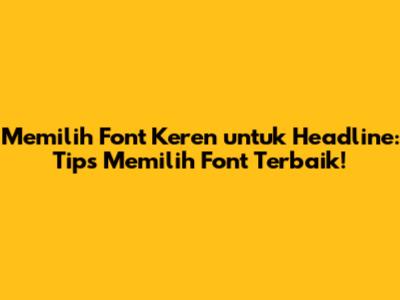
- Times New Roman: Font klasik yang selalu menjadi pilihan aman.
- Georgia: Font serif yang lebih modern dan mudah dibaca di layar.
- Merriweather: Font serif yang elegan dan cocok untuk headline artikel berita.
- Playfair Display: Font serif yang mewah dan cocok untuk headline artikel fashion atau lifestyle.
- Arial: Font sans-serif yang paling umum dan mudah dibaca.
- Helvetica: Font sans-serif yang klasik dan sering digunakan dalam desain grafis.
- Roboto: Font sans-serif yang modern dan cocok untuk headline website.
- Montserrat: Font sans-serif yang stylish dan cocok untuk headline artikel teknologi.
- Bebas Neue: Font display yang tinggi dan ramping, cocok untuk headline yang ingin terlihat modern.
- Oswald: Font display yang tebal dan kuat, cocok untuk headline artikel olahraga.
- Lobster: Font display yang script dan unik, cocok untuk headline artikel kreatif.
- Pacifico: Font display yang casual dan menyenangkan, cocok untuk headline artikel anak-anak.
- Gunakan alat bantu: Ada banyak alat bantu online yang bisa membantu kamu memilih font yang tepat, seperti FontPair atau Typewolf.
- Lihat contoh: Coba lihat contoh headline dari website atau majalah yang kamu sukai. Perhatikan font yang mereka gunakan dan bagaimana mereka mengkombinasikannya.
- Uji coba: Setelah kamu memilih beberapa font, uji coba dengan headline artikel kamu. Lihat bagaimana tampilannya di berbagai perangkat dan ukuran layar.
- Minta pendapat: Minta pendapat dari teman atau kolega kamu tentang font yang kamu pilih. Pendapat dari orang lain bisa membantu kamu melihat dari sudut pandang yang berbeda.
Memilih font yang cocok untuk headline itu krusial banget, guys! Headline adalah kesan pertama yang dilihat pembaca, jadi pemilihan font yang tepat bisa bikin mereka langsung tertarik dan pengen baca lebih lanjut. Bayangin deh, kalau headline-nya aja udah nggak menarik, gimana mereka mau tertarik sama isi artikelnya? Makanya, yuk kita bahas gimana caranya milih font yang oke buat headline kamu!
Kenapa Pemilihan Font Headline itu Penting?
Headline itu kayak jendela toko buat artikel kamu. Kalau jendelanya menarik, orang pasti pengen masuk dan lihat-lihat, kan? Sama kayak headline, kalau font-nya menarik dan mudah dibaca, orang pasti penasaran dan pengen baca artikel kamu sampai selesai. Font yang tepat bisa mencerminkan tone dan gaya artikel kamu. Misalnya, kalau artikel kamu tentang teknologi, font yang modern dan futuristik bisa jadi pilihan yang pas. Sebaliknya, kalau artikel kamu tentang sejarah, font yang klasik dan elegan mungkin lebih cocok. Selain itu, font juga bisa membangun hierarki visual. Headline harus lebih menonjol daripada teks lainnya, jadi pemilihan font yang lebih besar, lebih tebal, atau lebih unik bisa membantu menciptakan perbedaan yang jelas. Dengan hierarki visual yang baik, pembaca bisa dengan mudah memahami struktur artikel kamu dan fokus pada informasi yang paling penting.
Nggak cuma itu, pemilihan font yang asal-asalan bisa bikin artikel kamu kelihatan nggak profesional. Bayangin deh, kalau kamu lihat website dengan desain yang berantakan dan font yang nggak jelas, pasti langsung ilfeel, kan? Sama halnya dengan artikel, kalau headline-nya nggak menarik atau sulit dibaca, orang bisa langsung skip artikel kamu. Jadi, investasi waktu dan tenaga untuk memilih font yang tepat itu penting banget buat meningkatkan kualitas dan kredibilitas artikel kamu.
Terakhir, pemilihan font yang tepat juga bisa meningkatkan SEO (Search Engine Optimization). Google dan mesin pencari lainnya memperhatikan faktor visual dalam menentukan peringkat artikel. Artikel dengan desain yang menarik dan mudah dibaca cenderung mendapatkan peringkat yang lebih tinggi. Jadi, dengan memilih font yang tepat, kamu nggak cuma bikin artikel kamu kelihatan lebih keren, tapi juga membantu meningkatkan visibilitasnya di mesin pencari.
Faktor-faktor yang Perlu Diperhatikan dalam Memilih Font
Sebelum kita masuk ke rekomendasi font, ada beberapa faktor penting yang perlu kamu perhatikan:
1. Keterbacaan (Readability)
Ini adalah faktor yang paling penting. Font yang kamu pilih harus mudah dibaca, terutama dalam ukuran besar. Hindari font yang terlalu rumit atau terlalu dekoratif, karena bisa bikin pembaca kesulitan membaca headline kamu. Pastikan huruf-hurufnya jelas dan spasi antar hurufnya cukup lebar. Coba deh, lihat headline di majalah atau website berita. Mereka biasanya menggunakan font yang sederhana dan mudah dibaca, seperti Arial, Helvetica, atau Times New Roman. Tapi, bukan berarti kamu harus selalu pakai font-font itu ya. Ada banyak font lain yang juga mudah dibaca dan punya karakter yang unik.
2. Kesesuaian dengan Topik dan Gaya
Font yang kamu pilih harus sesuai dengan topik dan gaya artikel kamu. Misalnya, kalau artikel kamu tentang fashion, font yang stylish dan elegan bisa jadi pilihan yang tepat. Sebaliknya, kalau artikel kamu tentang teknologi, font yang modern dan futuristik mungkin lebih cocok. Coba deh, bayangin kalau kamu baca artikel tentang sejarah dengan font yang futuristik, pasti aneh kan? Jadi, pastikan font yang kamu pilih mencerminkan isi dan suasana artikel kamu.
3. Kontras
Pastikan font kamu memiliki kontras yang cukup dengan latar belakang headline. Kalau latar belakangnya gelap, pilih font yang terang. Sebaliknya, kalau latar belakangnya terang, pilih font yang gelap. Kontras yang baik bisa memudahkan pembaca untuk membaca headline kamu. Hindari menggunakan warna font yang terlalu mirip dengan warna latar belakang, karena bisa bikin headline kamu sulit dibaca. Selain itu, perhatikan juga ukuran font. Headline harus lebih besar daripada teks lainnya, sehingga bisa menonjol dan menarik perhatian.